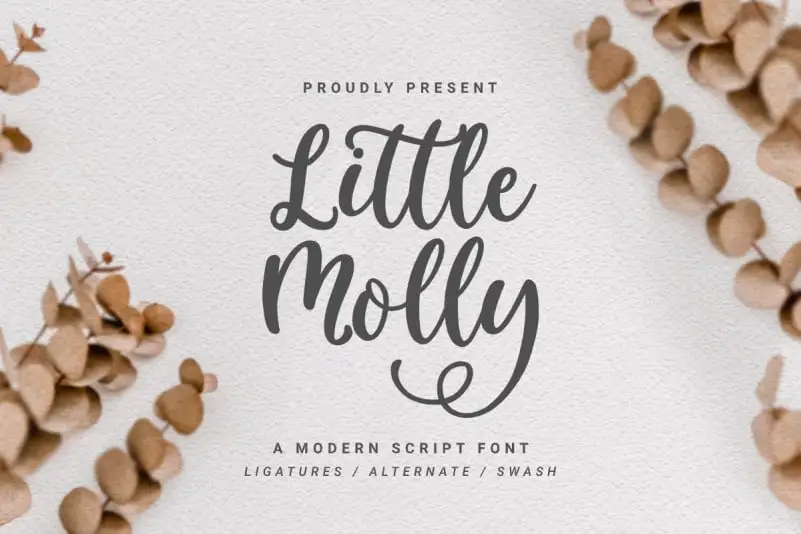
Little Molly Script Font – Download Grátis
Descubra a delicadeza e a elegância que só a fonte Little Molly Script pode trazer para seus projetos. Esta chamada ao estilo script é uma obra-prima, com suas letras distintas e perfeitamente redondas criando um design único. Ideal para aqueles que buscam algo romântico e sofisticado para personalizar seus projetos, seja em cartões de aniversário, cartazes ou até mesmo gráficos digitais. Little Molly Script não se limita a uma única função; ela se adapta com versatilidade para qualquer situação. Experimente e crie designs impressionantes! Este é mais do que apenas uma fonte: ele é um artefato de criação, pronto para transformar seus projetos em verdadeiras obras de arte. Você encontrará na Little Molly Script Font a perfeição da escrita manual, transformada em algo único e poderoso.